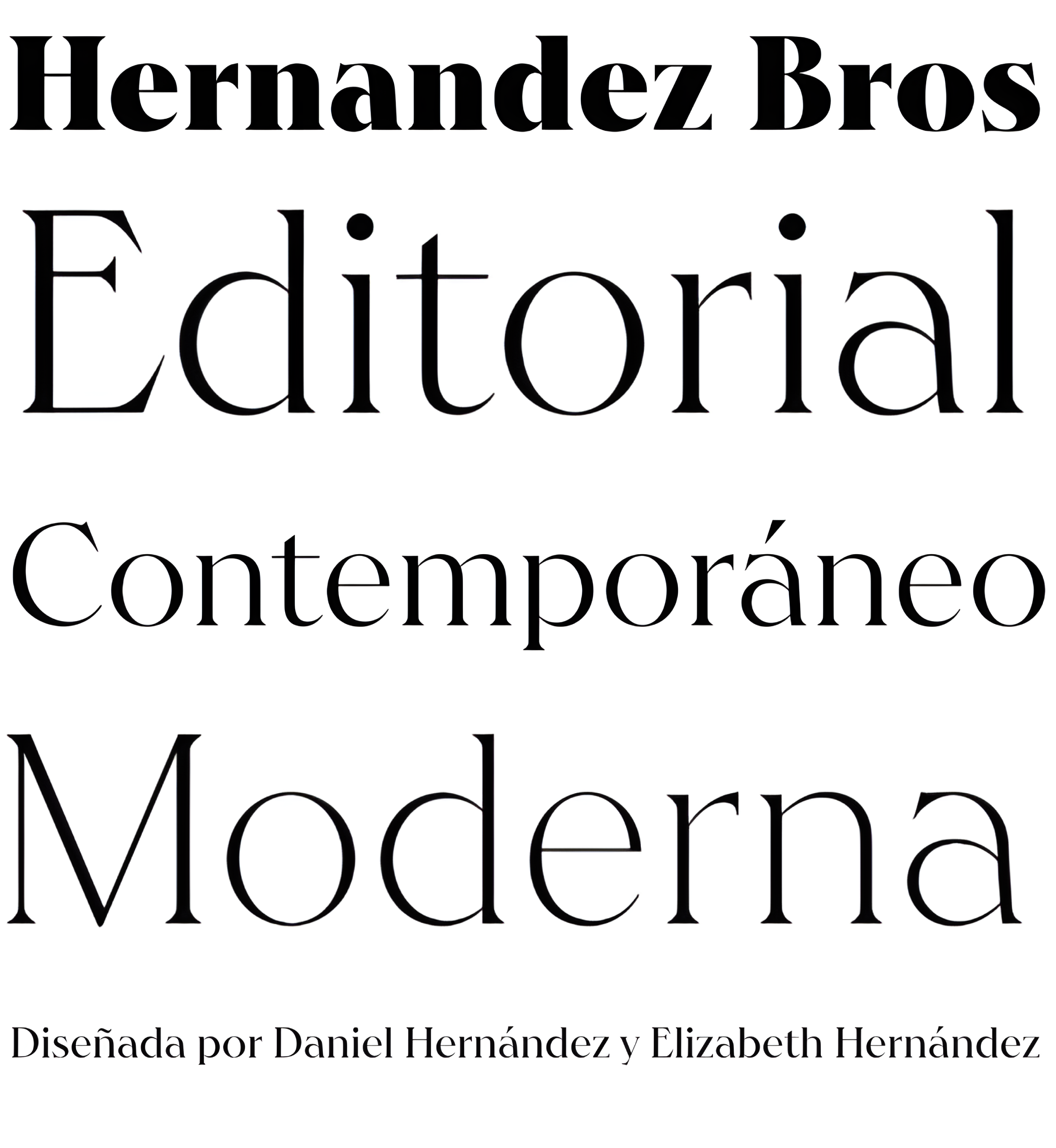
| Año | 2022 |
| Créditos | Daniel Hernández, Elizabeth Hernández |
| Descripción | Hernández Bros, es una tipografía diseñada por Daniel y Eli Hernández. Nace en el año 2021, en plena pandemia del Covid, de un espíritu colaborativo donde todo les llamaba a trabajar juntos como una familia, para obtener mejores resultados en tiempos tan difíciles. |
| Clasificación | Texto |
| Familia(s) | Hernandez Bros |
| Estilos | 8 |